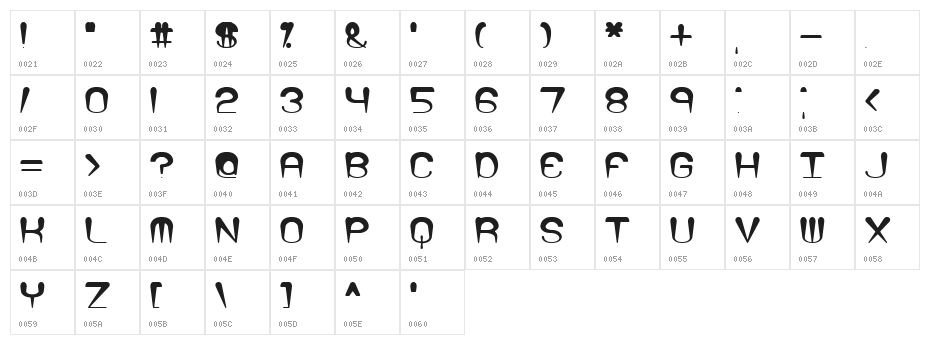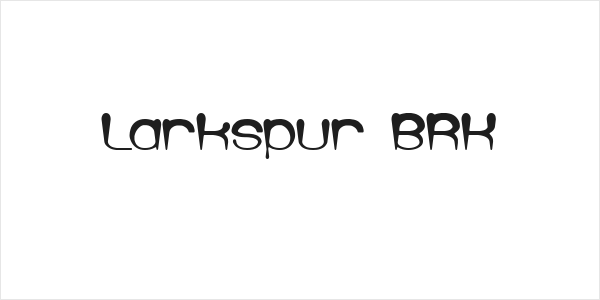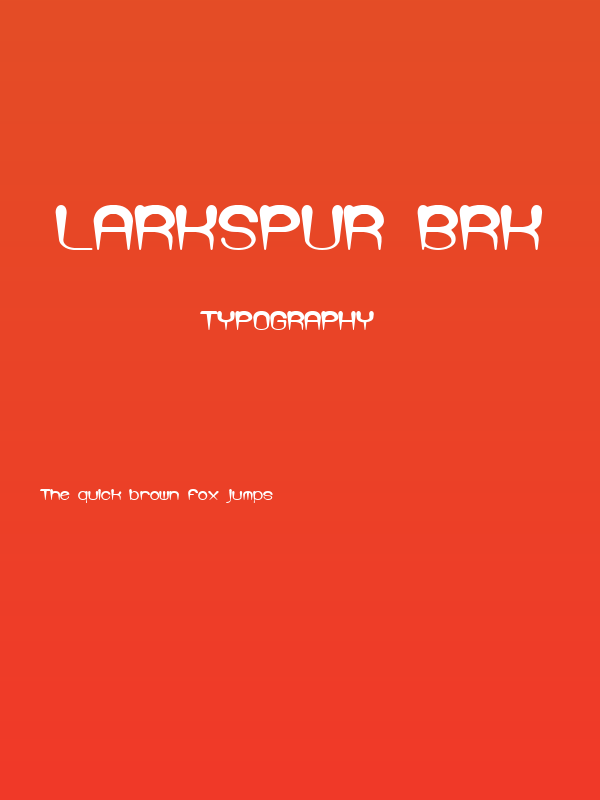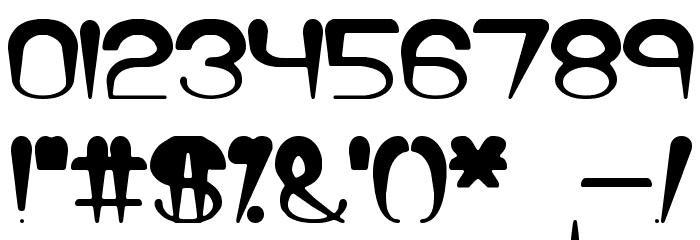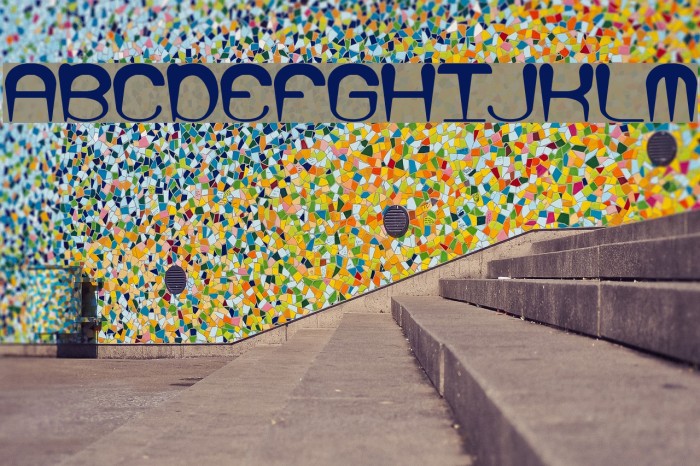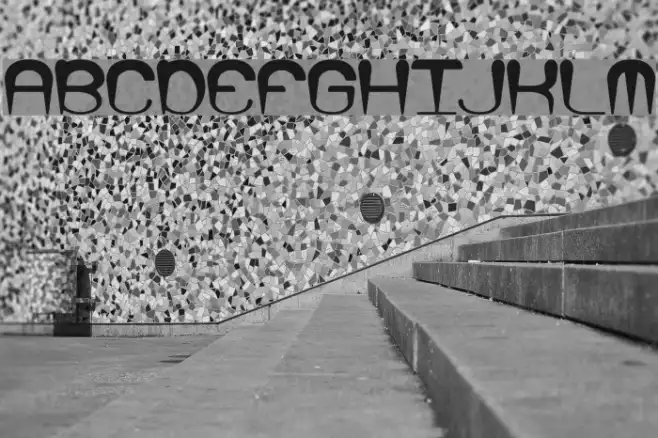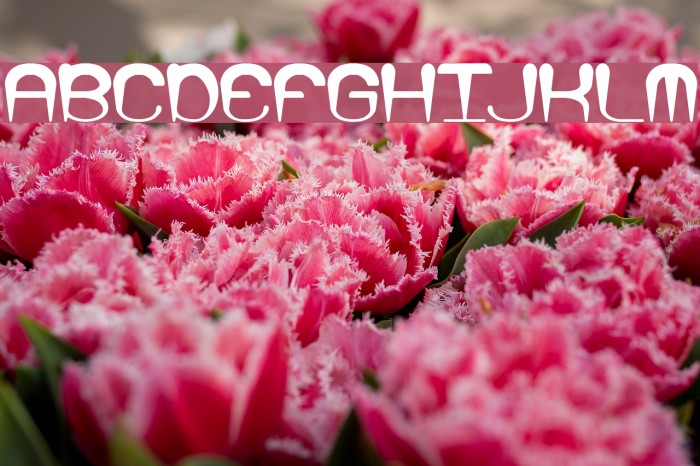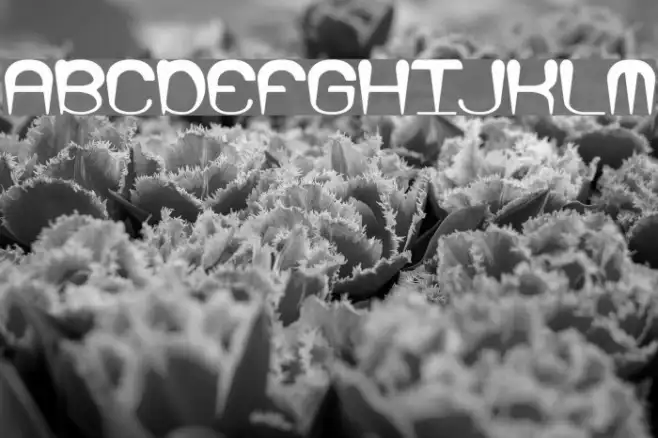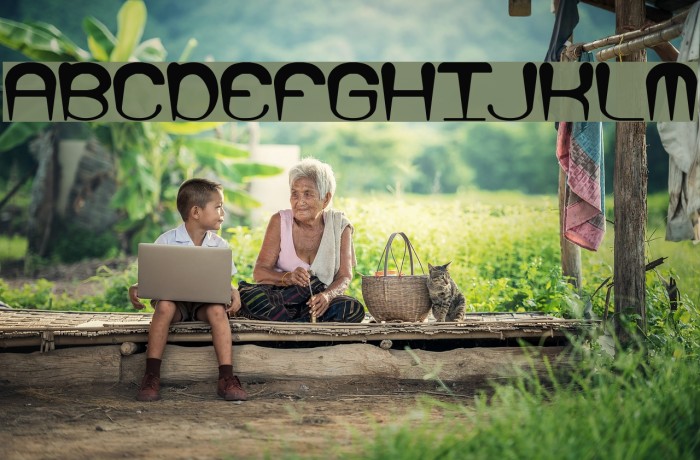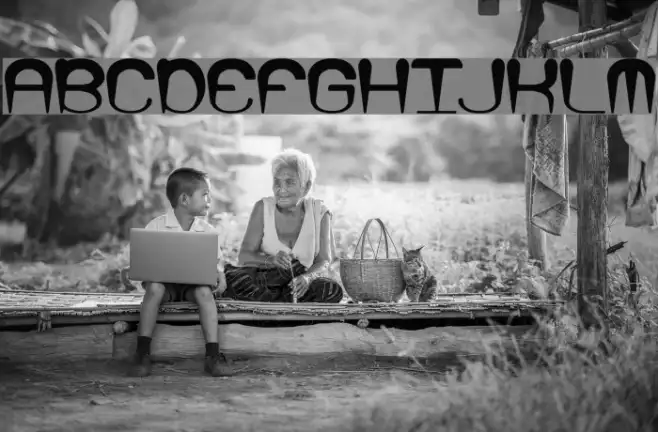
Larkspur BRK Font
| Gesamtstil | Playful, Whimsical, Creative |
| Vorgeschlagene Projekte | Ideal for children's books, playful branding, party invitations, and creative posters. |